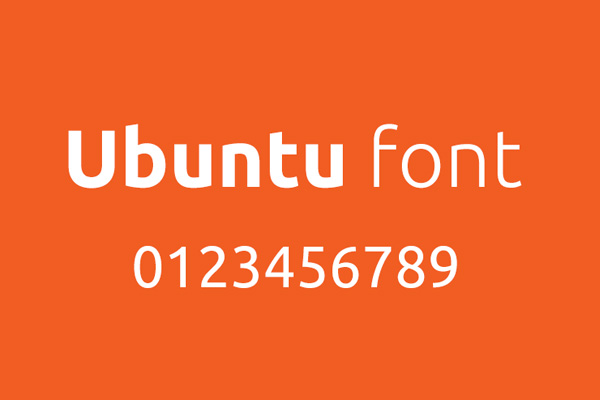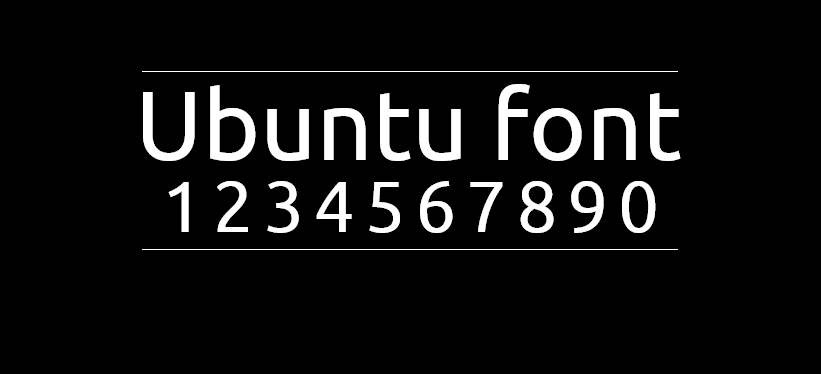
Ubuntu Font字体
Ubuntu是一款开源字体,可以免费用于商业用途。这款字体具有强烈的时尚感和无衬线设计,给人一种简洁、现代的感觉。同时,Ubuntu包含了正体、斜体等13种字形,满足了不同设计的需求。无论是制作海报、广告还是进行网页设计,Ubuntu都是一个非常合适的选择。因此,推荐使用Ubuntu字体,为您的设计增添一抹亮眼的风格。
Ubuntu Font开源字体效果预览
Ubuntu Font开源字体字体效果预览